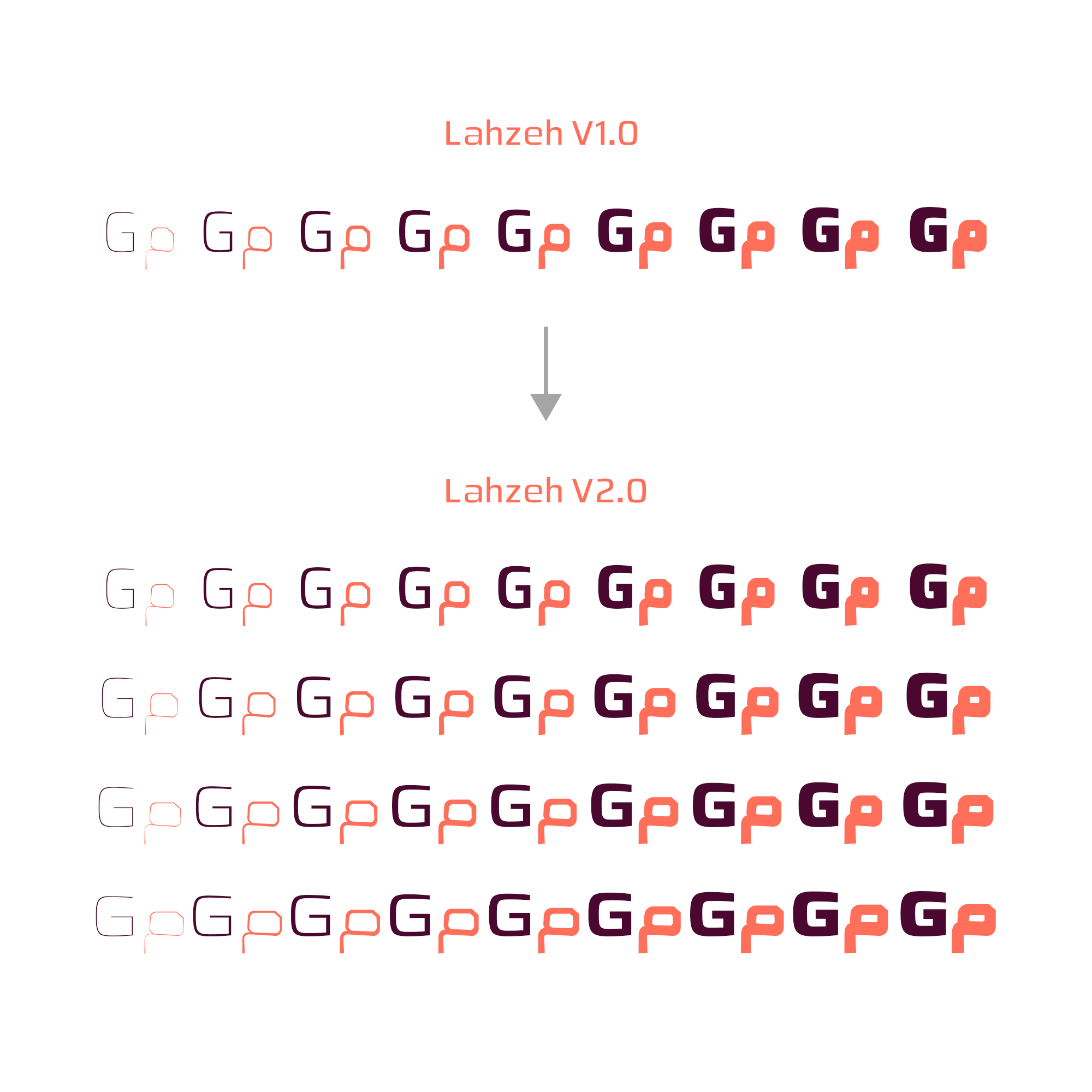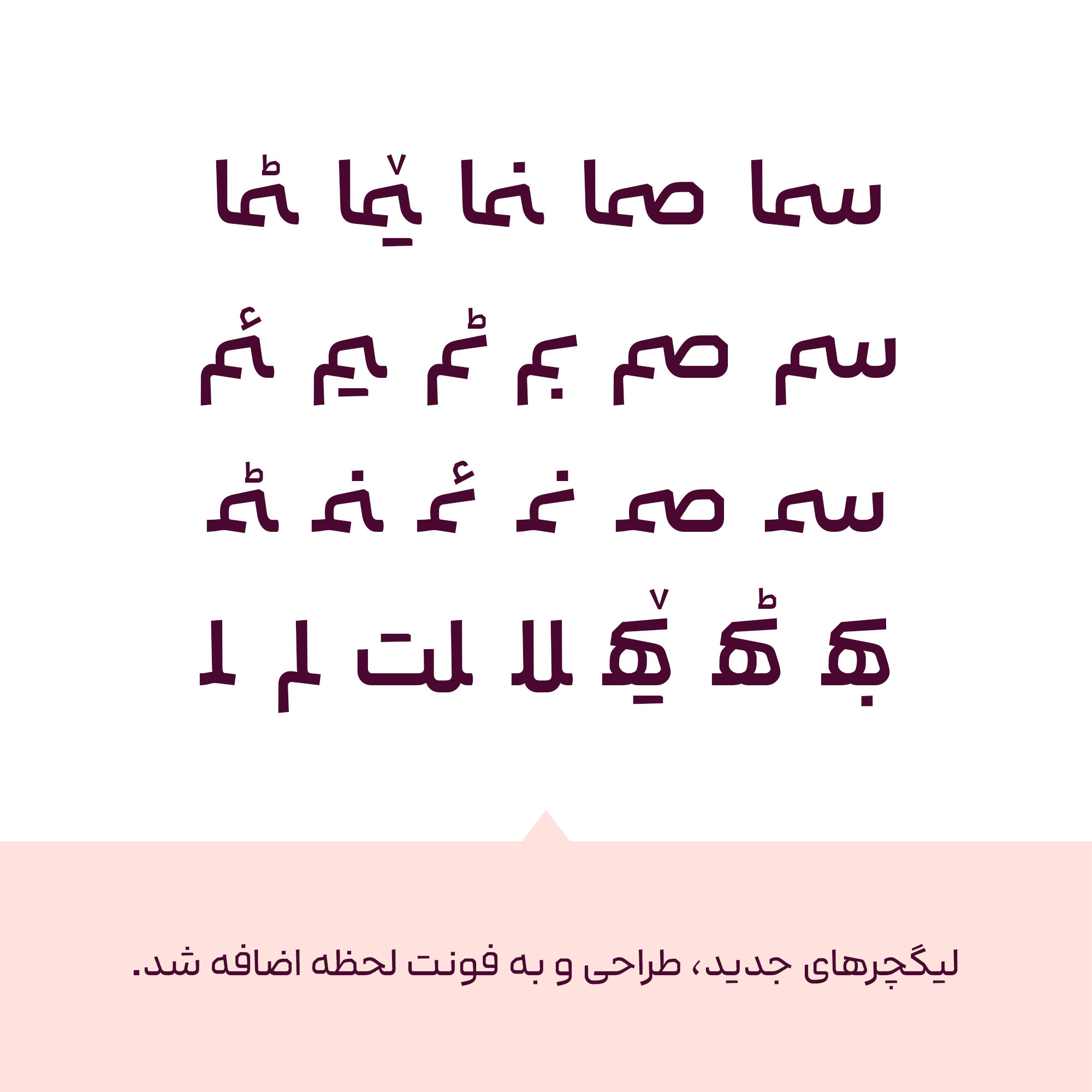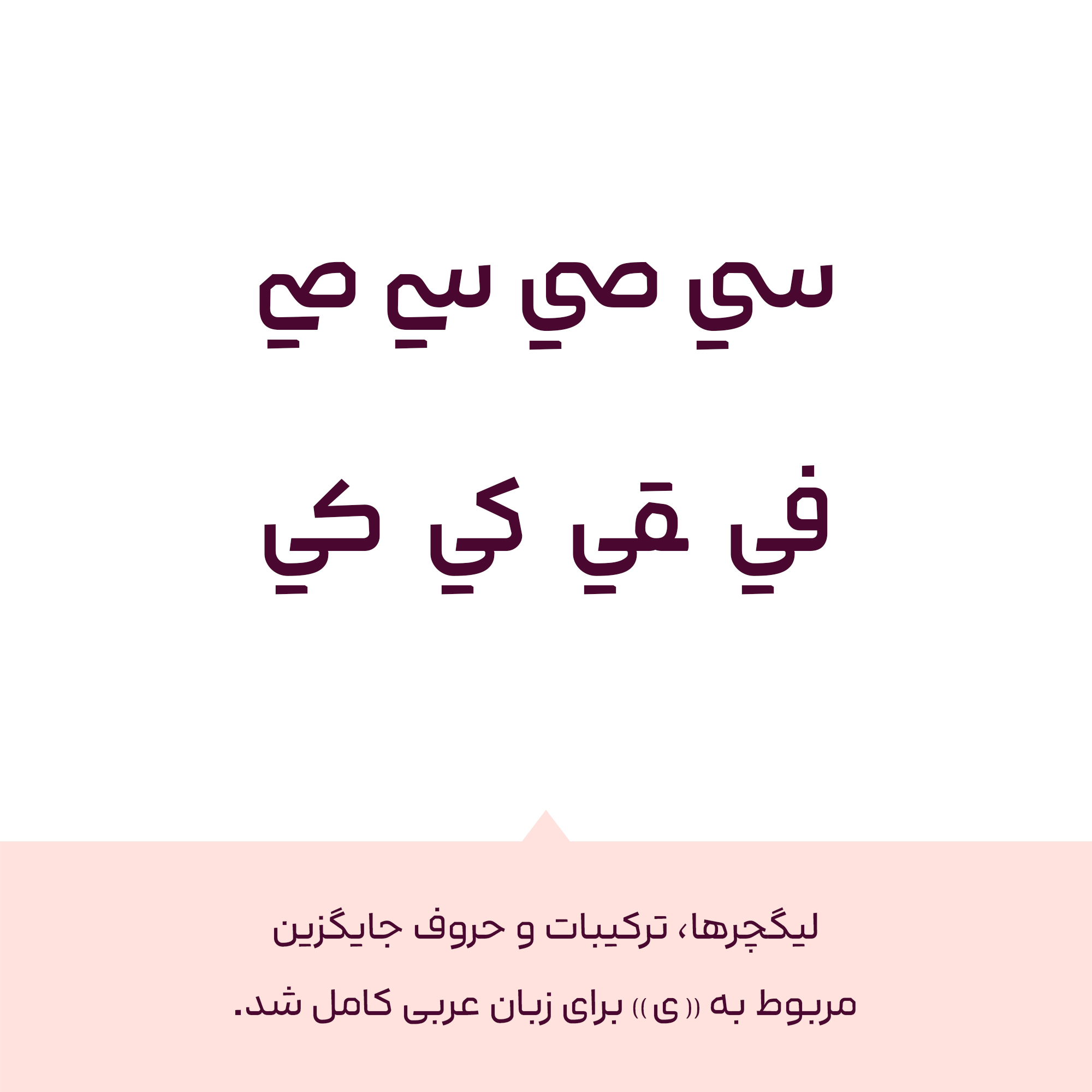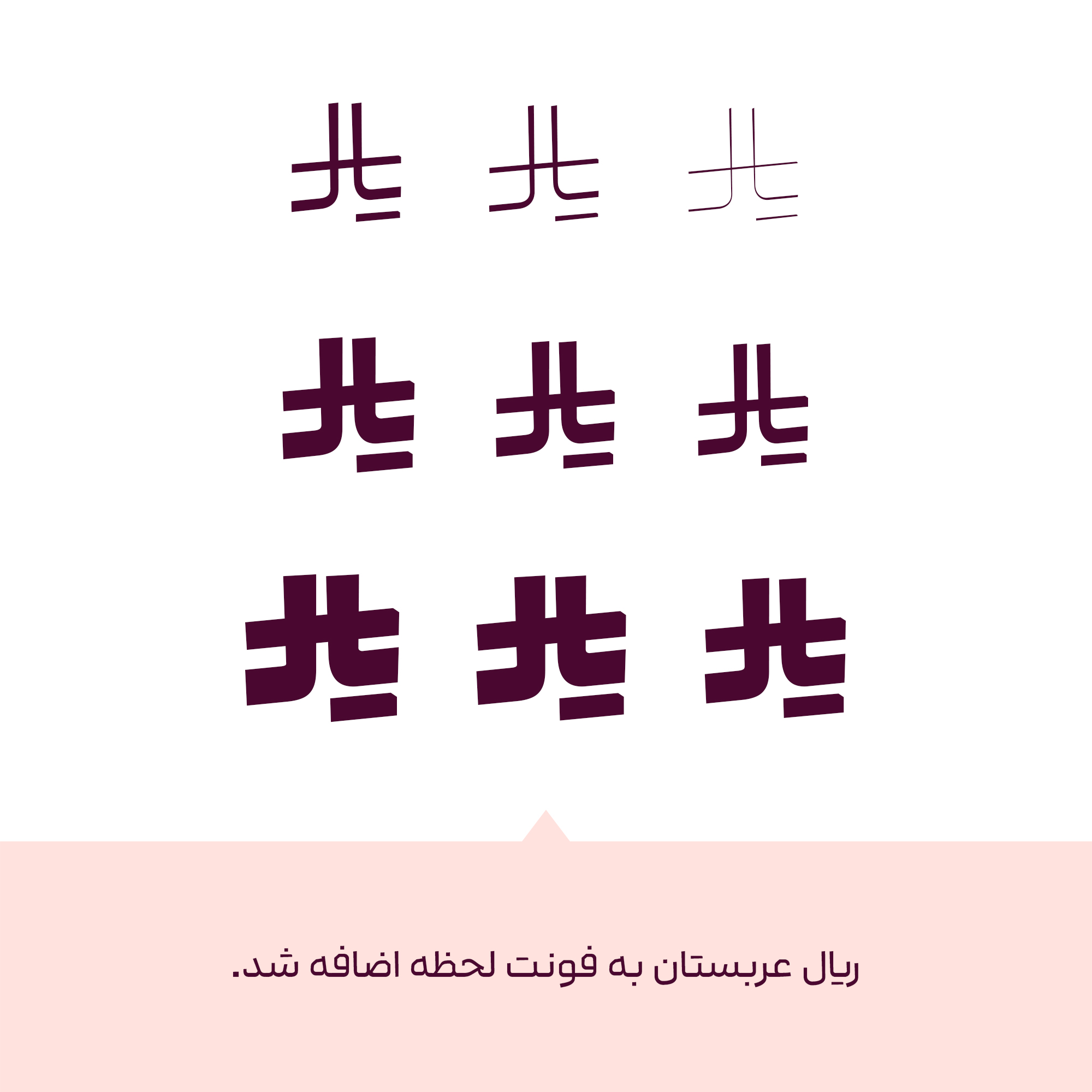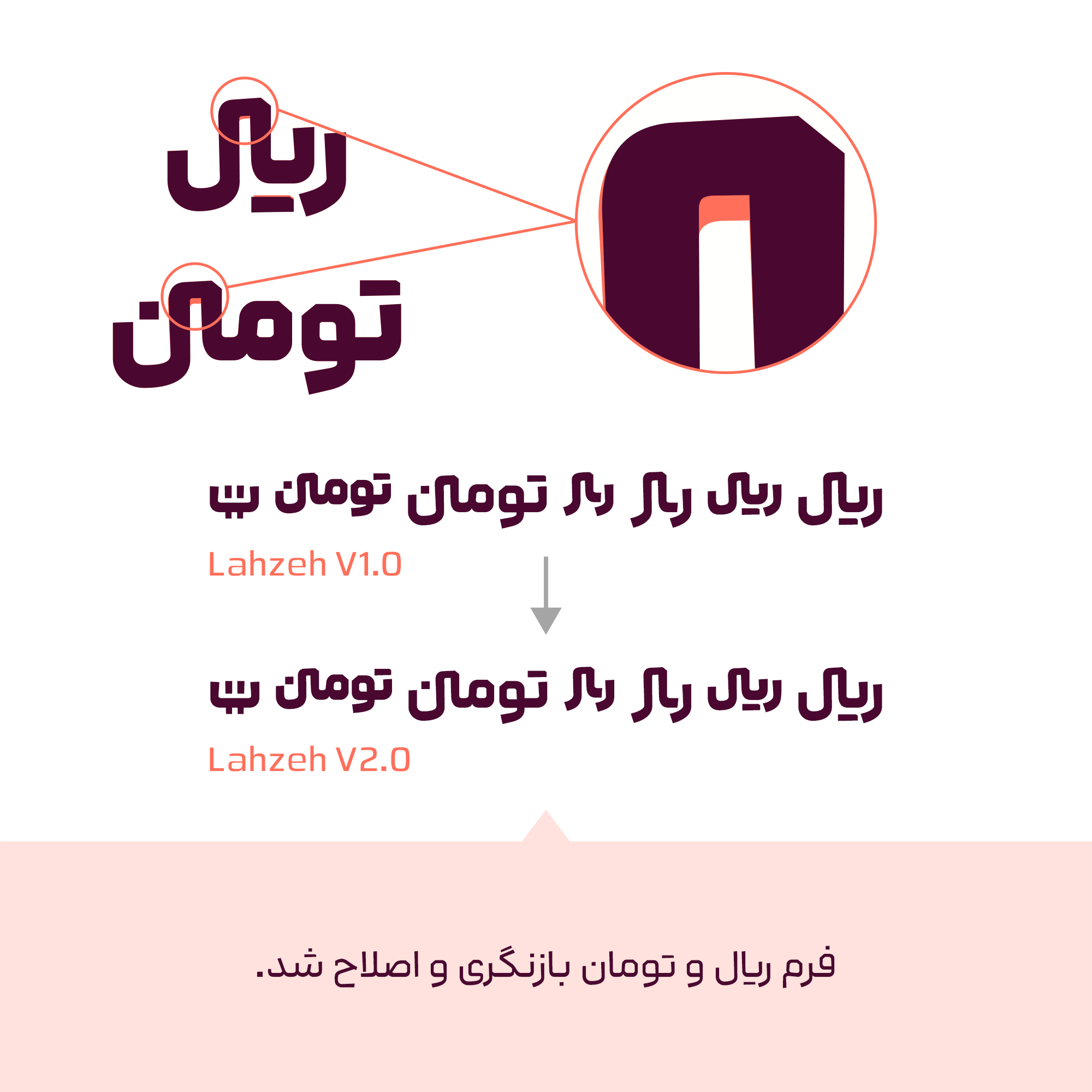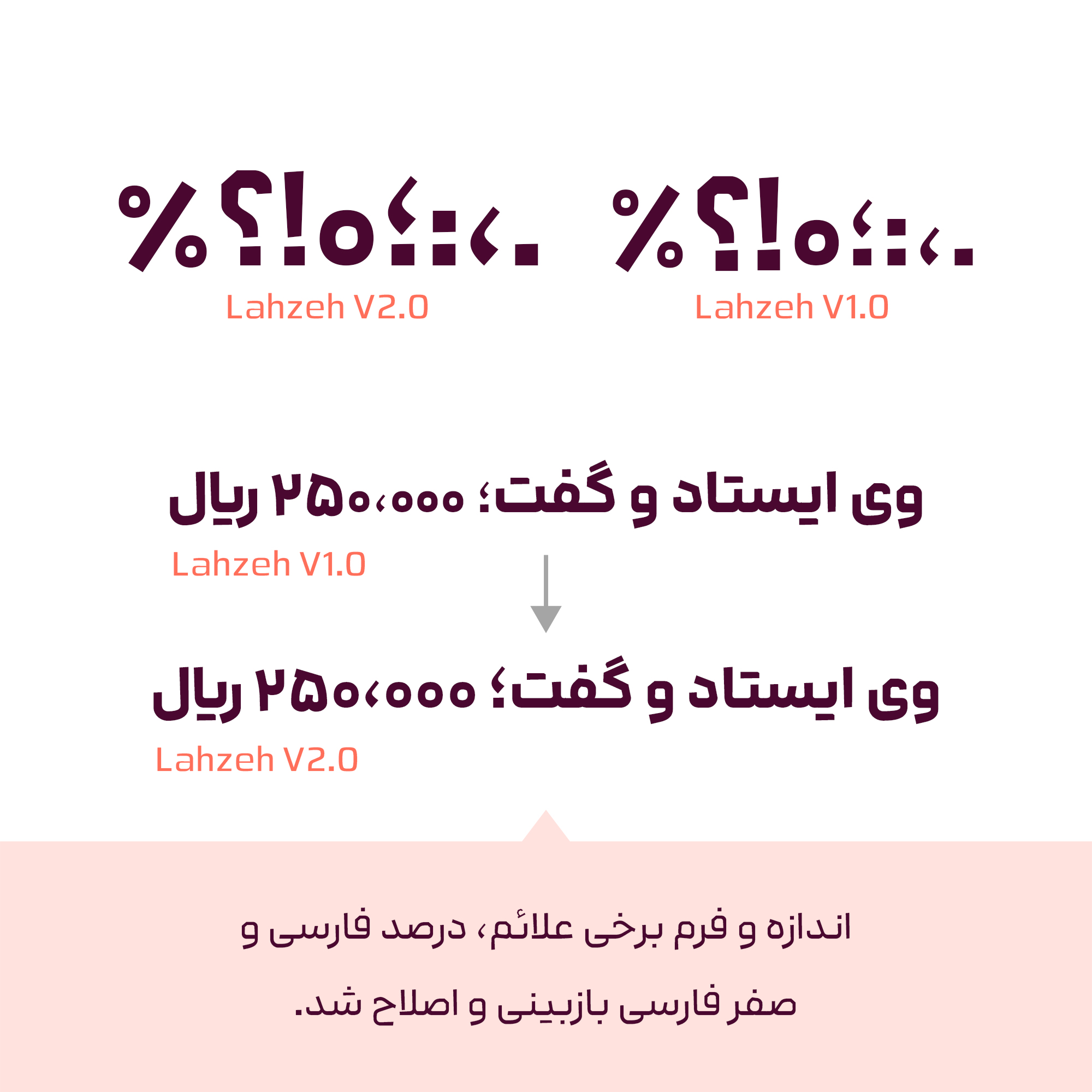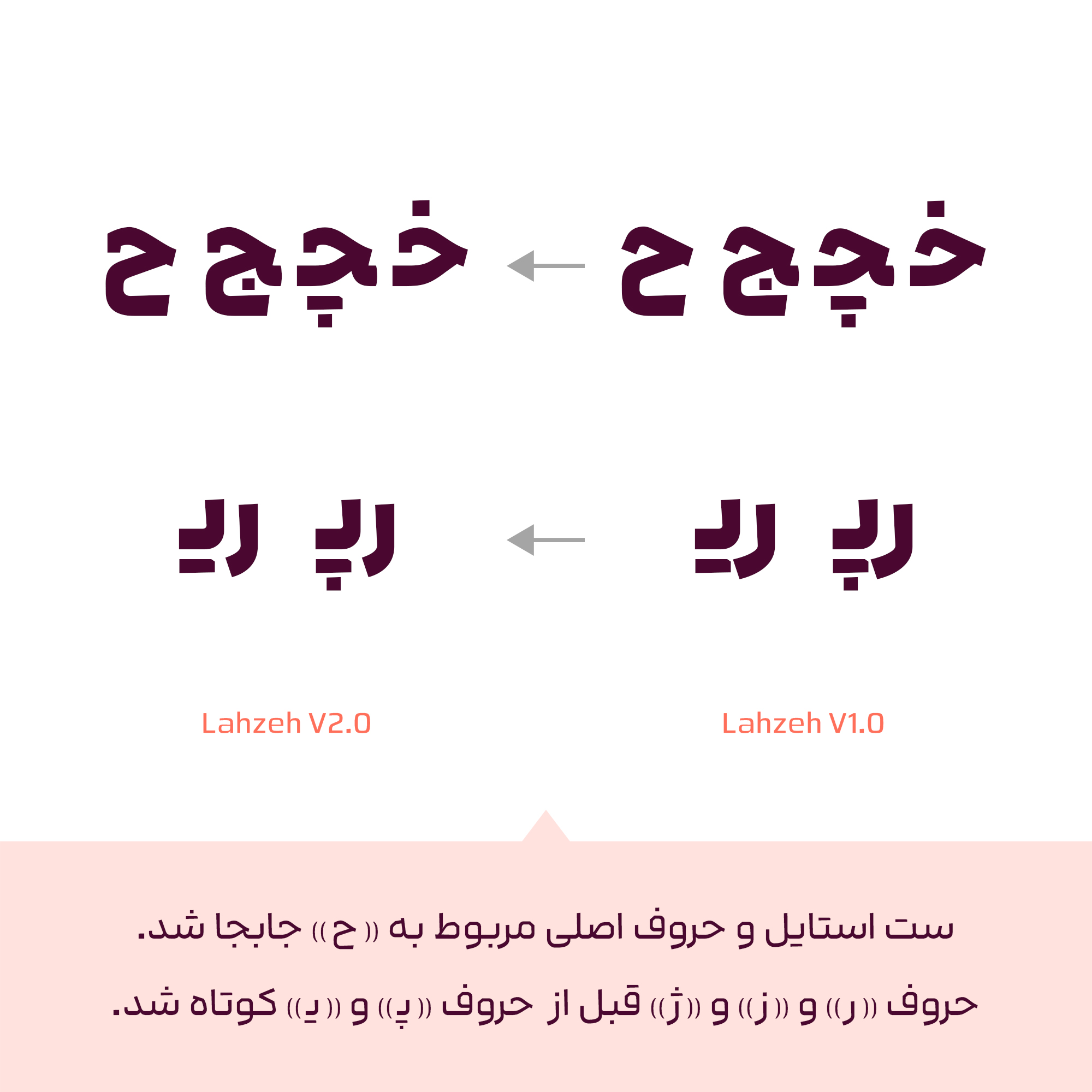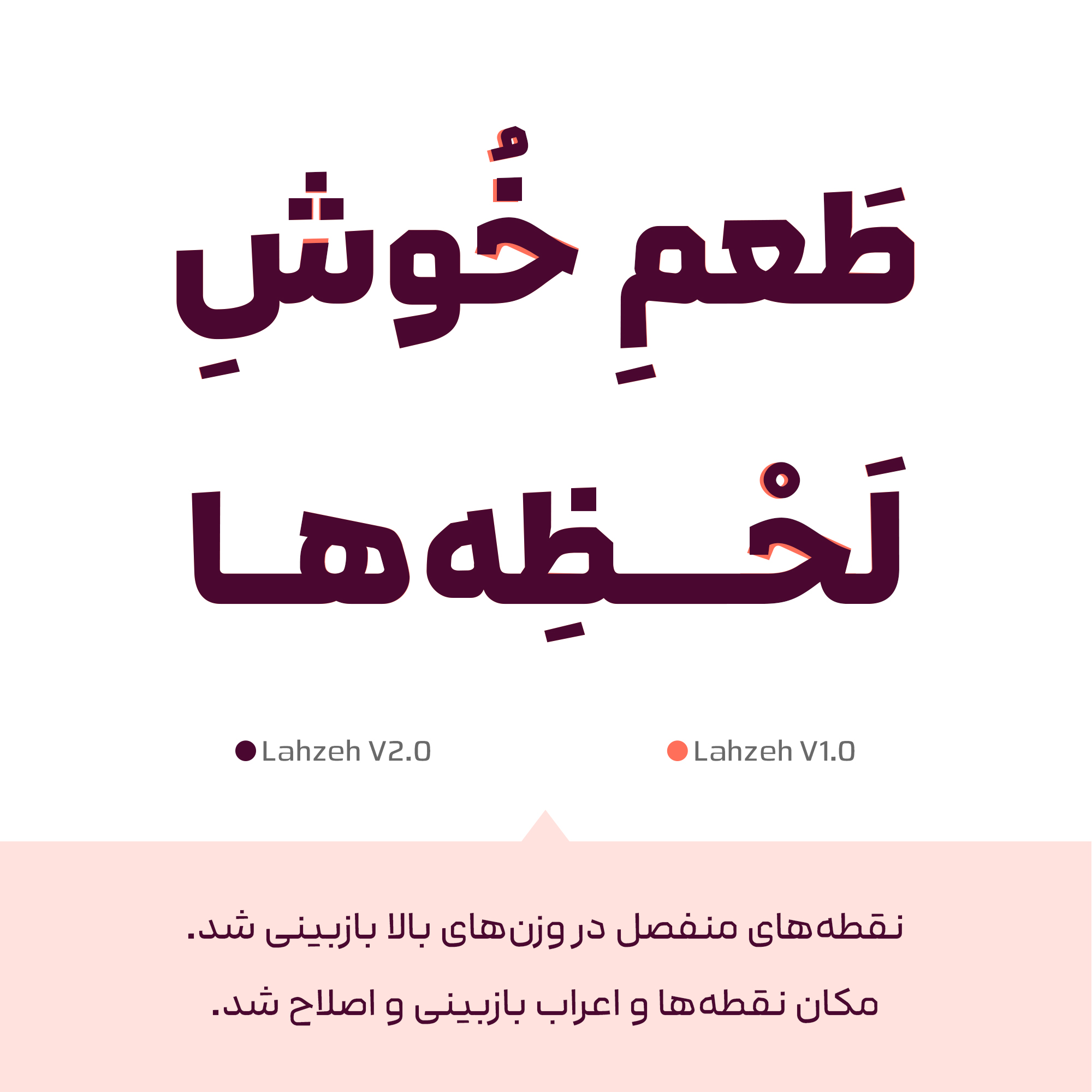
نسخه 2 فونت لحظه
- اضافه شدن 4 سطح کشیدیگی
- لیگچرهای جدید
- کامل شدن ترکیبات مربوط به حروف عربی
- اضافه شدن علامت ریال عربستان
- اصلاح فرم ریال و تومان
- اصلاح برخی از علائم
- کوتاه شدن اتصال "رزژ" به حروف "پـ یـ بـ " و اصلاح فرم " خـ چـ جـ حـ "
- بازبینی نقاط منفصل